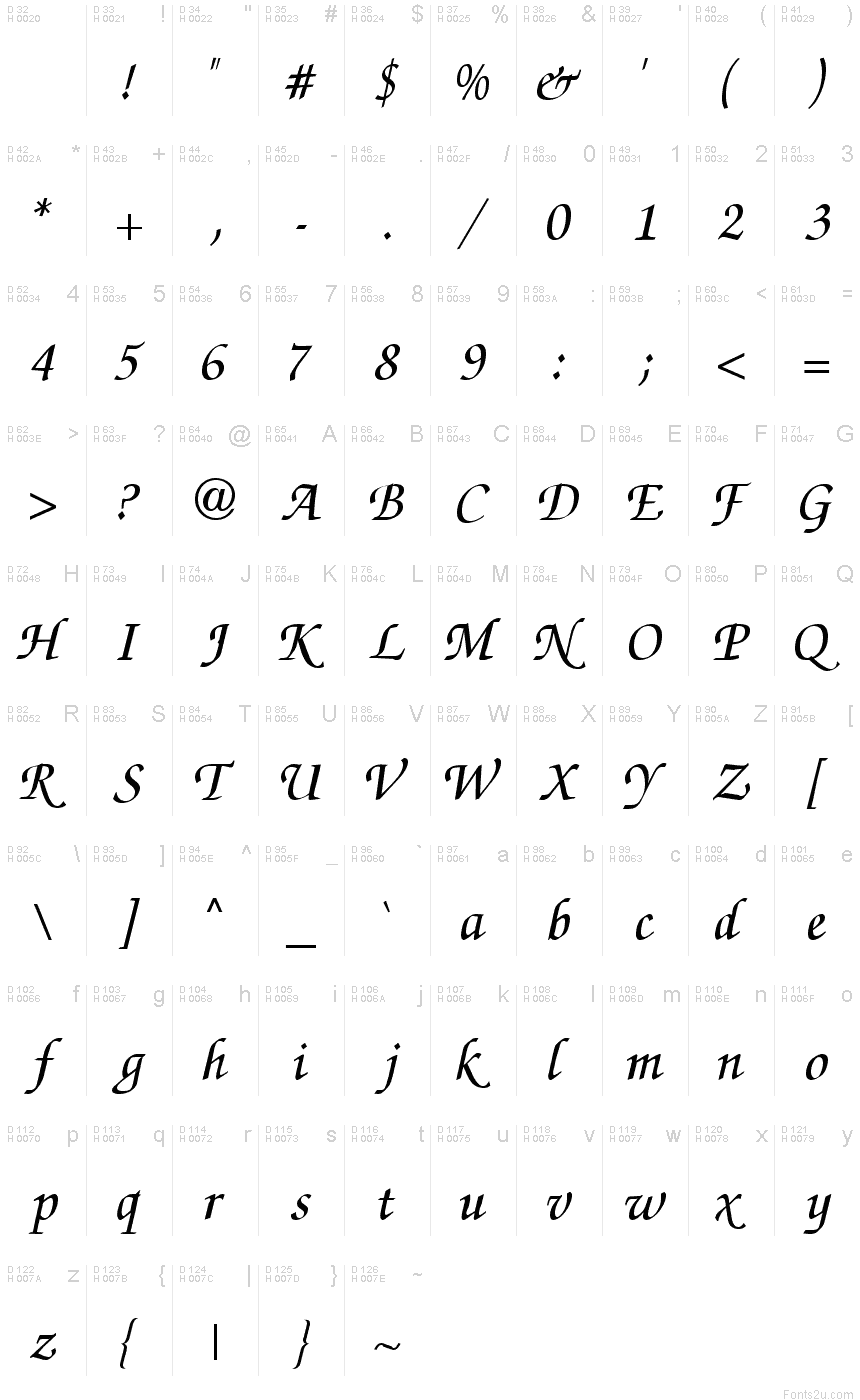
Invitation to darmowy, kaligraficzny krój szeryfowy, który przywodzi na myśl tusz na grubym papierze. Pochylone formy, ostre początki kresek i delikatnie zaostrzone krzywizny nadają każdemu słowu uroczysty charakter, przypominający starannie dopracowane pismo odręczne. Litery łączą się wizualnie, nie stykając się fizycznie, dzięki czemu tekst pozostaje wyrazisty i czytelny, zachowując jednocześnie osobisty, ciepły wyraz.
Używając Invitation, nagłówki stają się eleganckie i formalne, nie tracąc przy tym lekkości. Dzięki temu ten darmowy font jest naturalnym wyborem dla zaproszeń ślubnych i okolicznościowych, menu, certyfikatów, metek prezentowych oraz identyfikacji wizualnej butików. Krój ten prezentuje się znakomicie w większych rozmiarach, gdzie jego zamaszyste przekątne i zwężające się linie mogą w pełni wybrzmieć. W przypadku tekstu głównego lub drobnych detali, połącz Invitation z czytelnym, bezszeryfowym krojem o mniejszym stopniu pisma, aby zachować elegancję i czytelność.